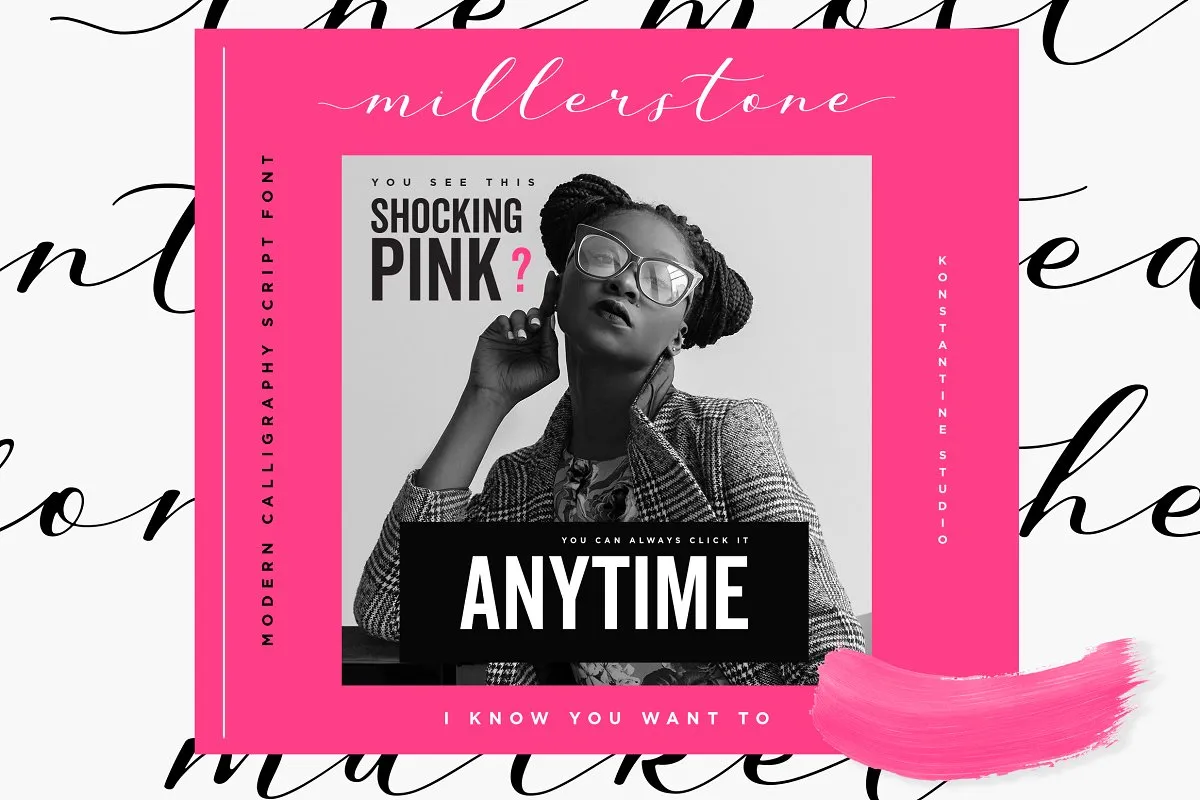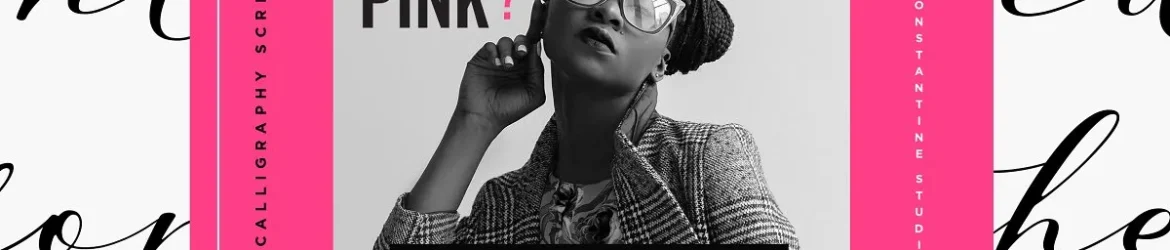
Millerstone Calligraphy Font – Download Grátis
A Millerstone Calligraphy Font é uma elegante tipografia de script parafeituoso que combina modernidade com feminilidade sofisticada. Perfeita para anúncios de festas natalinas e ocasiões especiais, a Millerstone também se destaca em projetos como cartões de casamento, material de estação, logotipos e conceitos fashion. Suave e atraente, ela combina perfeitamente com linhas serifadas para destacar palavras importantes ou complementa outros elementos gráficos em ambientes de marca casual mas sofisticada — seja um logo, uma campanha publicitária, conteúdo digital ou até mesmo nas redes sociais. Inspirada no visual criativo da moda experimental, a Millerstone é perfeita para seus projetos que valorizam a essência moderna e feminina.